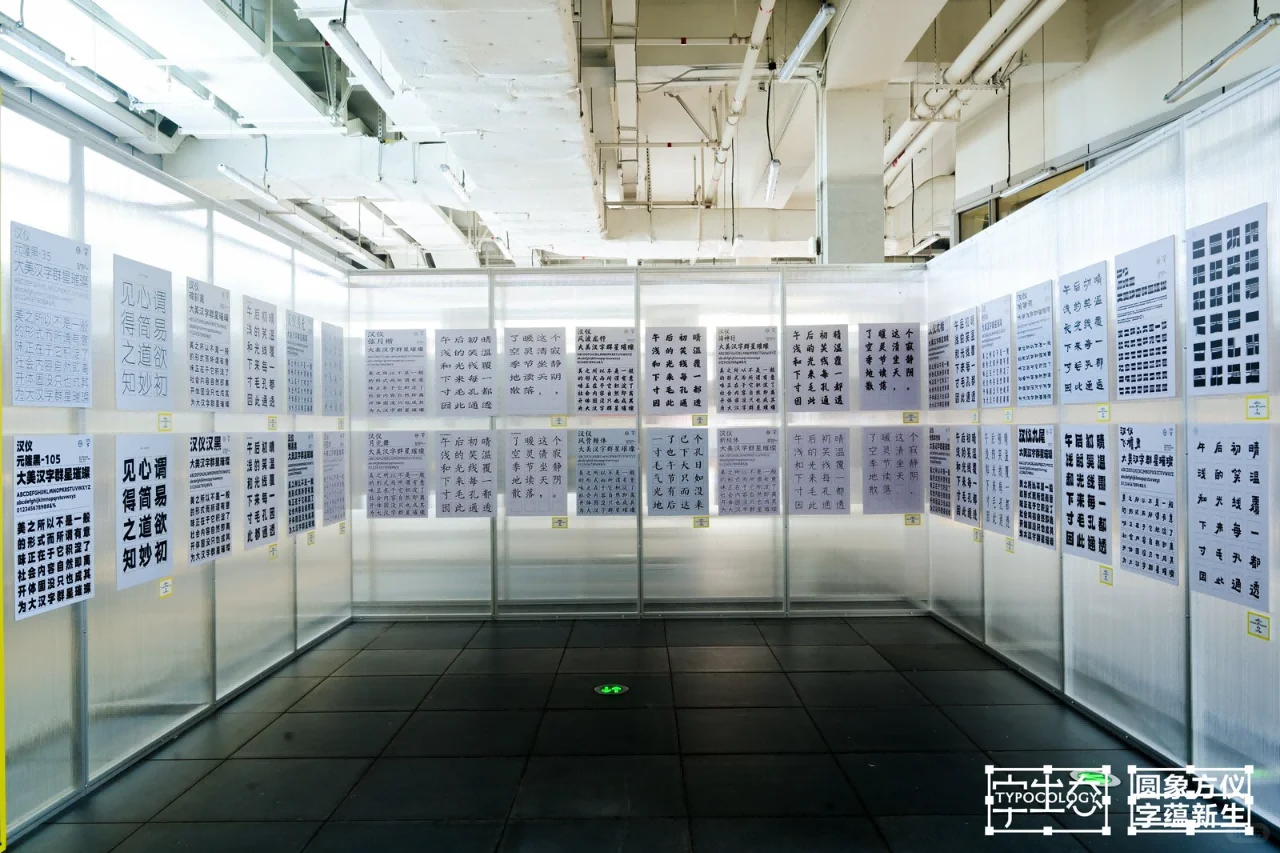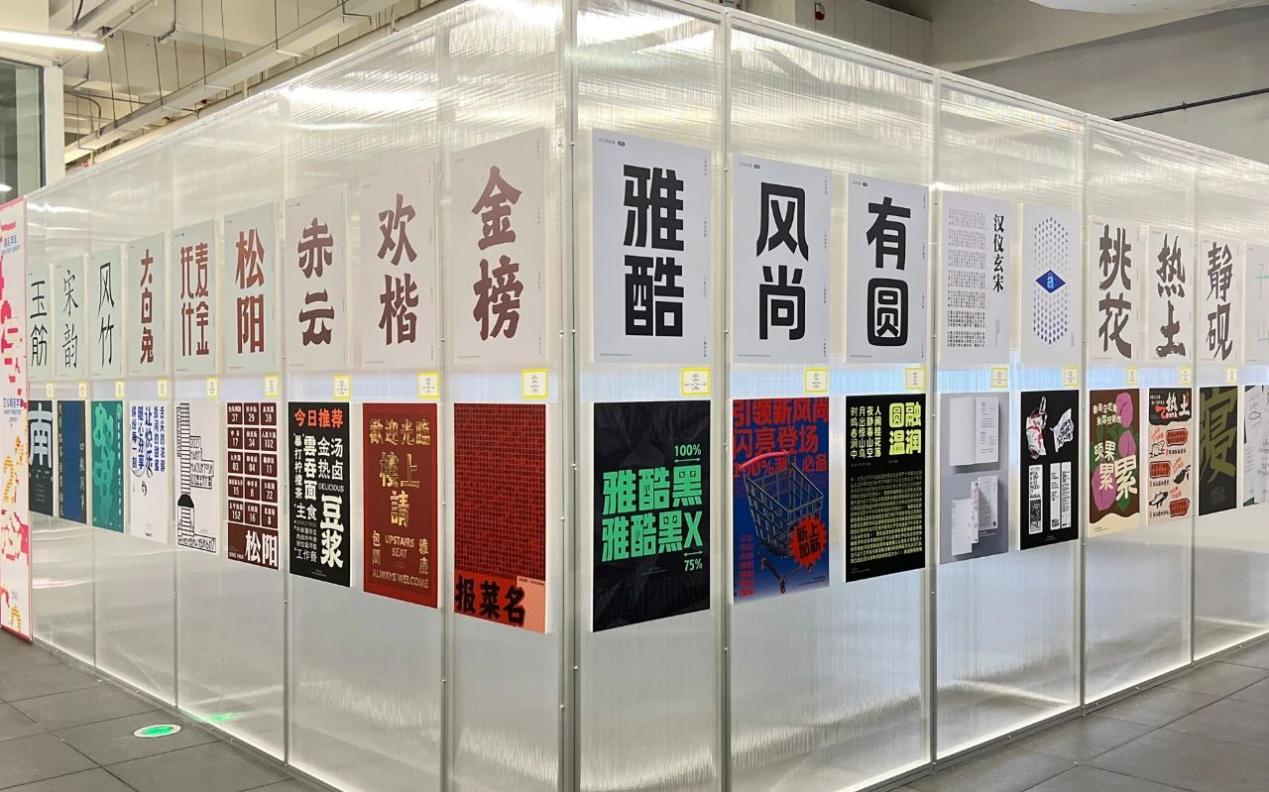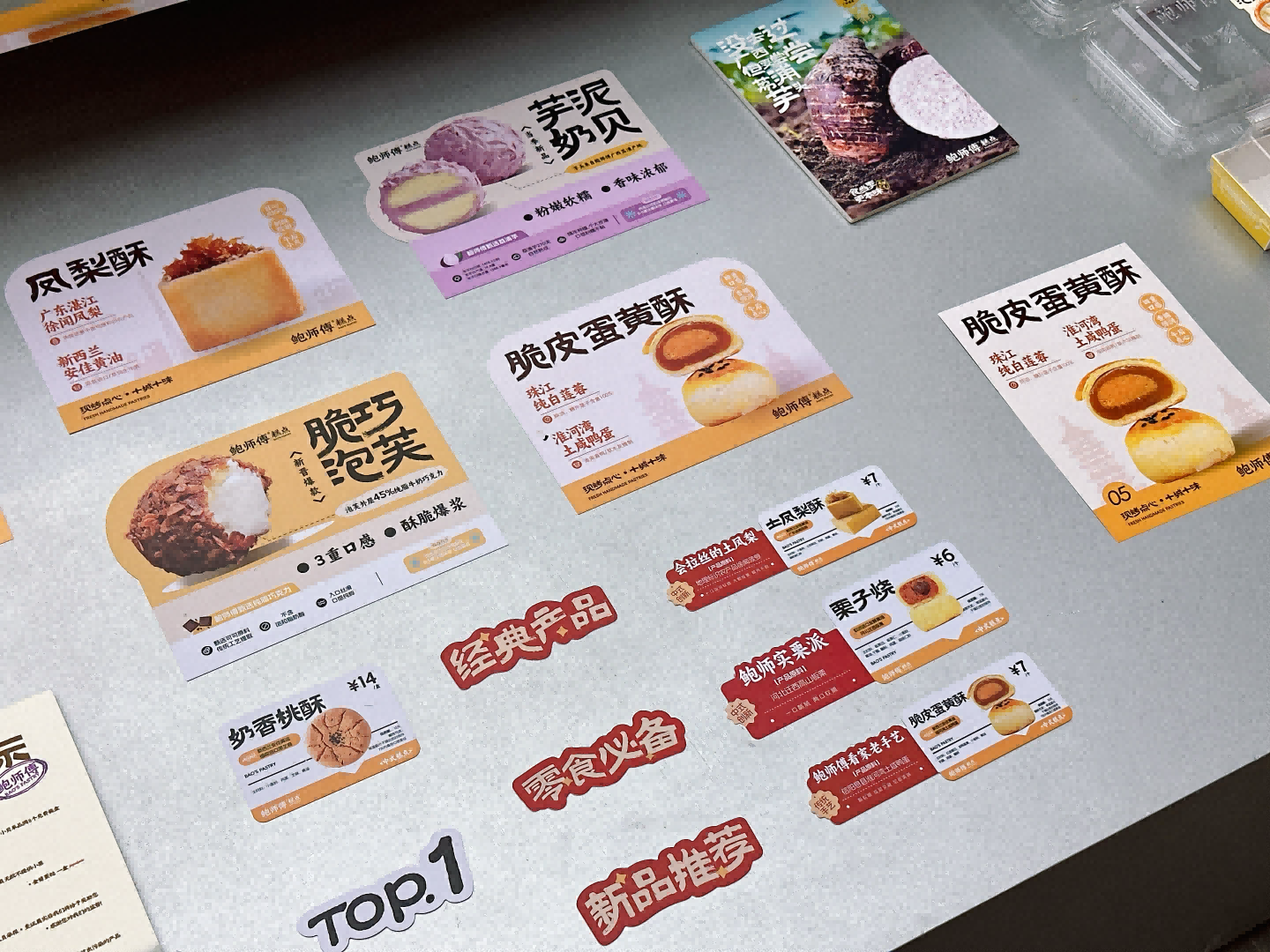
2024年11月27日,由深圳市平面设计协会(SGDA)、汉仪字库、方正字库、昊格高定字联合主办,甲古文创意设计有限公司、深圳大学国家形象研究中心(NIRC)、万科云城联合协办的“圆象⽅仪·字蕴新⽣——2024字生态设计展”正式启幕。本次展览旨在促进学术研究与商业实践的结合,重点探讨“文字美学”的三个维度——“形式之美”、“实用之美”和“适用之美”,以此推动文字文化的传承与创新。 汉仪字库作为主办方参与策展、展会讨论、参展等环节,以专业姿态,共同启程更好的字体未来。
字启未来,字体未来观察与实践探索
2024字生态设计展以“圆象方仪·字蕴新生”为主题,承接文字发展脉络,集学术性、艺术性和商业性于一体,它不仅仅是对过去成果的回顾与总结,更是对未来趋势的展望与探索;汉仪字库品牌与市场中心总监赵蕾以《字体未来观察与实践探索》为主题,进行总结分享。2024年初,在中国艺术科技研究所的指导下,汉仪字库和中国美术学院创新设计学院共同发布了《2024字体未来观察报告》,总结了字体设计的年度趋势和年度观察结果。回顾汉仪《2024字体未来观察报告》中总结的趋势与见解,以汉仪在2024年字体设计中的实践为脉络,探究“诗意新中式”、“复古新摩登”、“人文新烟火”年度趋势在当前字体设计中的应用。
汉仪字库在2024年践行《字体未来观察报告》,打造多款热门字体,以年度趋势与年度观察为脉络,其中汉仪文润宋韵聚焦古文古籍数字化再创,让传统古籍焕发新生;除此之外,汉仪字库与盖娅传说、东方腔调等文娱行业联合,针对音乐、服饰等多领域展开探索,完成“汉仪东方腔调”在内的联名字库,多角度欣赏中式汉字之美。
学术对谈,共话未来
“学术对谈”环节中,赵蕾、张昊、王贝宁、谢瑞康、梁佳、张涛、吕晓萌、刘文八位特邀嘉宾参与对谈。通过对经典案例的分析与解读,希望激发更多的思考与讨论,促进文字设计领域的健康发展。
迎合字体新发展机遇
在当今数字化、智能化的大潮中,文字设计正迎来前所未有的发展机遇。本次设计展通过与汉仪字库在内的多加业界领先企业合作,汇聚了众多优秀的设计师及作品,展现了文字设计的多元面貌。无论是传统的书法艺术,还是现代的数字字体,都在此寻得属于自己的位置,共同讲述着文字的故事,传递中华文化的精神内核。
本次汉仪参展字体繁多,以《字体未来观察报告》与汉仪字体之星历届获奖作品为展品脉络,展出了共计50余款字库作品。包括汉仪经典字库产品、汉仪字体之星历届获奖作品,韶音品牌定制字体ShokzSans在其高端礼盒上的设计应用,以及老字号糕点品牌鲍师傅使用“汉仪杰龙桃花源”的产品包装等众多实物展品,和字库作品,充分展示多样字体生态。
以字体设计为契机,让文字更好地传承下去,在文字“设计”与“日用”两个不同维度,汉仪将以全方位的姿态,迎合更新的字体发展,从而激发字体视觉的审美先行作用,发挥其时代审美风尚的触角与触媒力量。